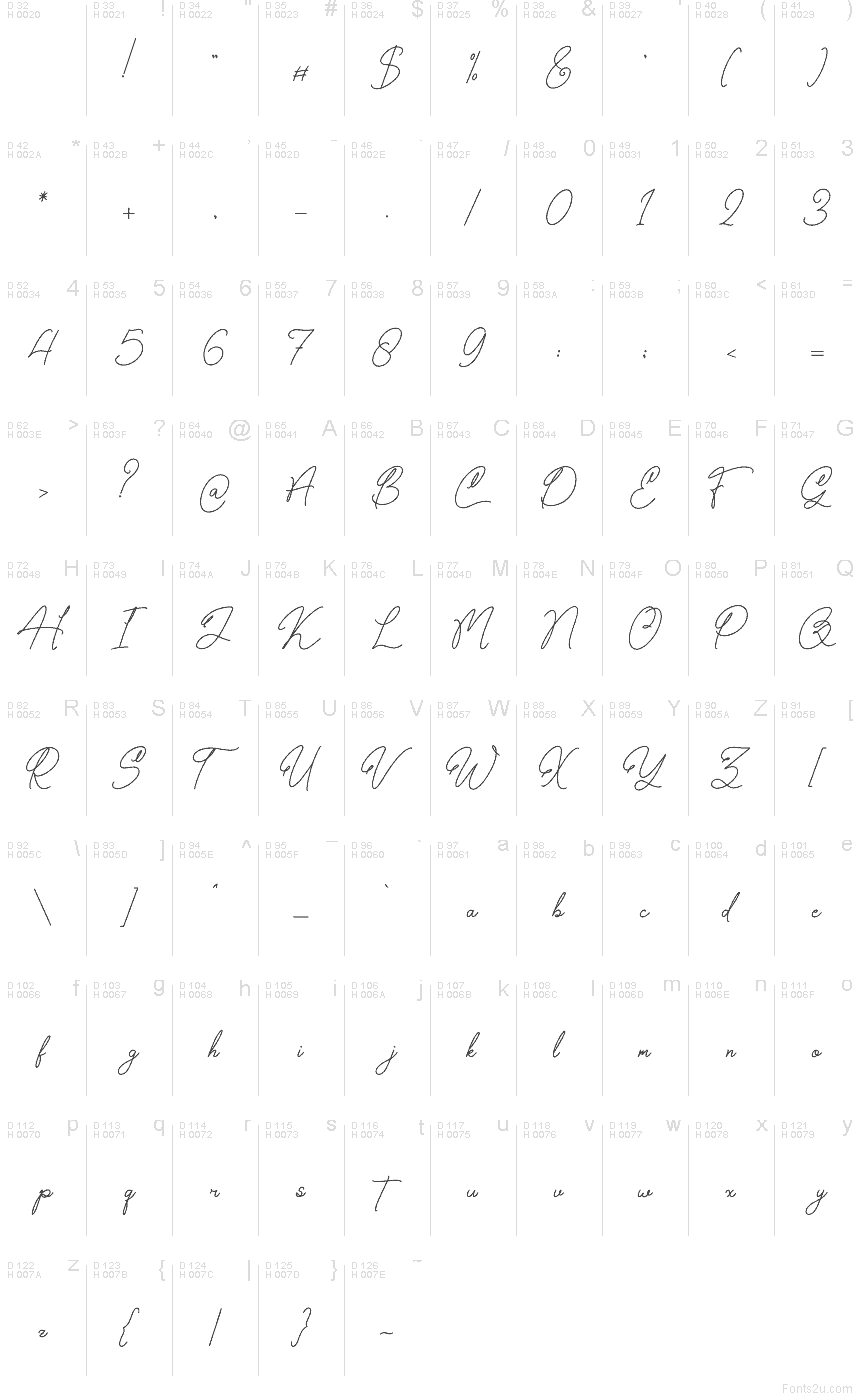
Chettalbury, bezplatné ručně psané písmo od Gracetype Studios, se nese ve vzdušném kaligrafickém rytmu, který je definován dlouhými smyčkami a táhlými vodorovnými tahy. Písmo působí dojmem, že bylo vykresleno jedním jistým tahem, kde vysoké dotažnicové prvky a široké křivky vytvářejí lehkou, plynulou siluetu, která je mnohem působivější než běžné neformální písmo.
Toto tempo dodává krátkým názvům, butikovým logům, nadpisům pozvánek, detailům obalů i grafice na sociálních sítích osobitý nádech. Skvěle se hodí také na karty s citáty nebo svatební tiskoviny, kde tyto roztažené tahy elegantně rámují text bez potřeby jakýchkoli dalších ozdob.